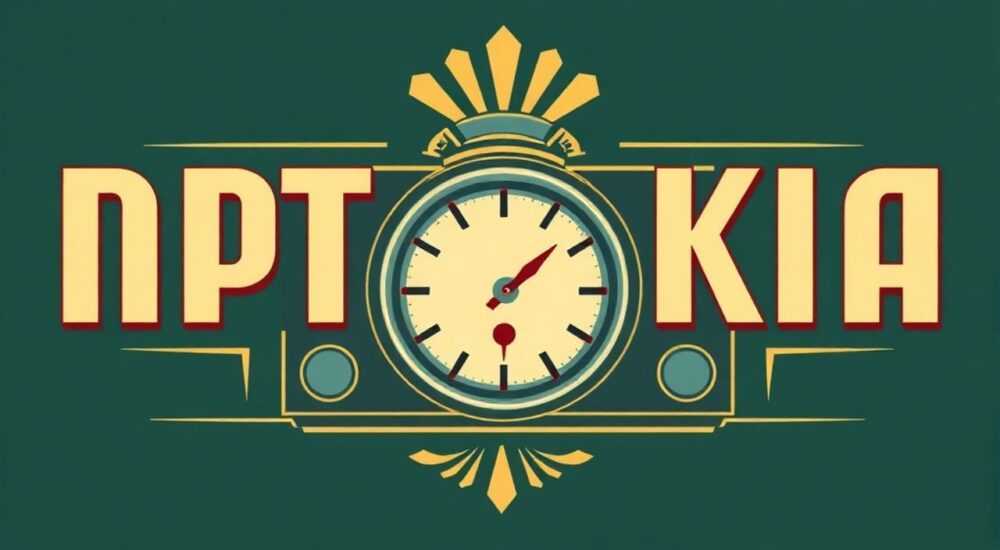
Шрифт ар деко кириллица
Ар-деко — это стиль, который зародился в 1920-х годах и до сих пор продолжает вдохновлять дизайнеров по всему миру. Особую роль в этом стиле играет типографика, которая отражает его характерные черты: роскошь, геометричность и модернизм. Но как быть, если вам нужен шрифт ар-деко в кириллической версии? Этот вопрос становится особенно актуальным для русскоязычных дизайнеров и брендов, стремящихся сохранить аутентичность стиля при работе с кириллицей. В этой статье мы подробно разберем особенности шрифтов ар-деко на кириллице, рассмотрим примеры использования и дадим практические рекомендации для работы с ними.
История стиля ар-деко и его влияние на типографику
Ар-деко возник как смелый ответ на излишнюю декоративность ар-нуво. Этот стиль олицетворял собой эпоху джаза, процветания и технологического прогресса. В типографике он проявился через четкие геометрические формы, контрастные линии и элементы декора, напоминающие о древних цивилизациях. Особенно ярко эти черты проявились в плакатах, рекламе и оформлении интерьеров 1920-1930-х годов.
Развитие шрифтов ар-деко происходило параллельно с появлением новых технологий печати. Именно в этот период появились первые беззеркальные шрифты, которые стали основой для современных геометрических гарнитур. Однако большинство классических шрифтов ар-деко создавались исключительно для латиницы, что создавало определенные трудности для адаптации стиля в странах с другими алфавитами.
Полезно знать: Первые попытки адаптации ар-деко под кириллицу начались в Советском Соагитпропе в 1930-х годах, когда потребовалась современная типографика для массовой пропаганды.
Особенности шрифтов ар-деко в кириллическом написании
Кириллическая версия шрифтов ар-деко имеет свои уникальные характеристики:
• Геометрическая основа с четкими углами и строгими формами
• Контраст между толстыми и тонкими элементами букв
• Наличие декоративных элементов в виде засечек или узоров
• Вытянутые вертикальные пропорции некоторых символов
• Особое внимание к сложным буквам кириллицы (Ж, Щ, Ы)
Создание качественной кириллической версии требует особого подхода. Дизайнер должен не только сохранить характерные черты стиля, но и обеспечить удобство чтения на русском языке. Это особенно важно для длинных текстов или информационных материалов.
Важная особенность современных шрифтов ар-деко — их универсальность. Они могут успешно использоваться как в цифровых медиа, так и в печатных материалах, сохраняя свою читаемость и стиль на разных устройствах и носителях.
Популярные шрифты ар-деко с поддержкой кириллицы
Шрифт
Основные характеристики
DecoType Cyrillic
Классический дизайн с богатым набором декоративных элементов
ArtDeco Pro Cyrillic
Модернизированная версия с улучшенной читаемостью
CyrDeco Modern
Современная интерпретация с упрощенными формами
Важное замечание: При выборе шрифта обратите внимание на наличие всех необходимых глифов и символов, особенно если планируется использование в многоязычных проектах.
Где и как использовать такие шрифты
Шрифты ар-деко с поддержкой кириллицы находят широкое применение в различных сферах дизайна:
• Логотипы и фирменный стиль компаний премиум-класса
• Оформление ресторанов, баров и ночных клубов
• Дизайн упаковки для люксовых товаров
• Создание рекламных материалов и афиш
• Декоративное оформление интерьеров
Особенно эффективно эти шрифты работают в следующих случаях:
• Когда нужно передать атмосферу роскоши и гламура
• В проектах, связанных с исторической тематикой 1920-1930-х годов
• Для создания контраста с современными минималистичными элементами
«Не стоит использовать шрифты ар-деко для больших объемов текста. Они лучше всего работают в заголовках и акцентных элементах.» — Мария Петрова, типографический дизайнер с 12-летним опытом
Советы по выбору и применению
При работе с шрифтами ар-деко на кириллице следует помнить несколько важных правил:
• Выбирайте шрифт, соответствующий масштабу вашего проекта
• Обращайте внимание на качество отрисовки каждой буквы
• Тестируйте шрифт на разных устройствах и носителях
• Сочетайте с простыми, нейтральными шрифтами для основного текста
• Учитывайте культурные особенности целевой аудитории
Частые ошибки при использовании шрифтов ар-деко:
• Перегрузка дизайна декоративными элементами
• Использование слишком мелкого размера шрифта
• Неправильное сочетание с другими типами шрифтов
• Игнорирование особенностей восприятия кириллических символов
«Современные шрифты ар-деко с поддержкой кириллицы — это не просто дань моде, а мощный инструмент в руках дизайнера. Главное — правильно использовать их потенциал. Например, при создании логотипа ресторана советской эпохи, такой шрифт может стать идеальным решением, передающим дух времени.» — Александр Иванов, арт-директор дизайн-студии «Ретро-Модерн», эксперт с 15-летним стажем
Частые вопросы
• Как отличить качественный шрифт ар-деко? Обратите внимание на детализацию букв, наличие всех необходимых глифов и общую гармонию форм. Качественный шрифт должен хорошо читаться и выглядеть одинаково хорошо во всех размерах.